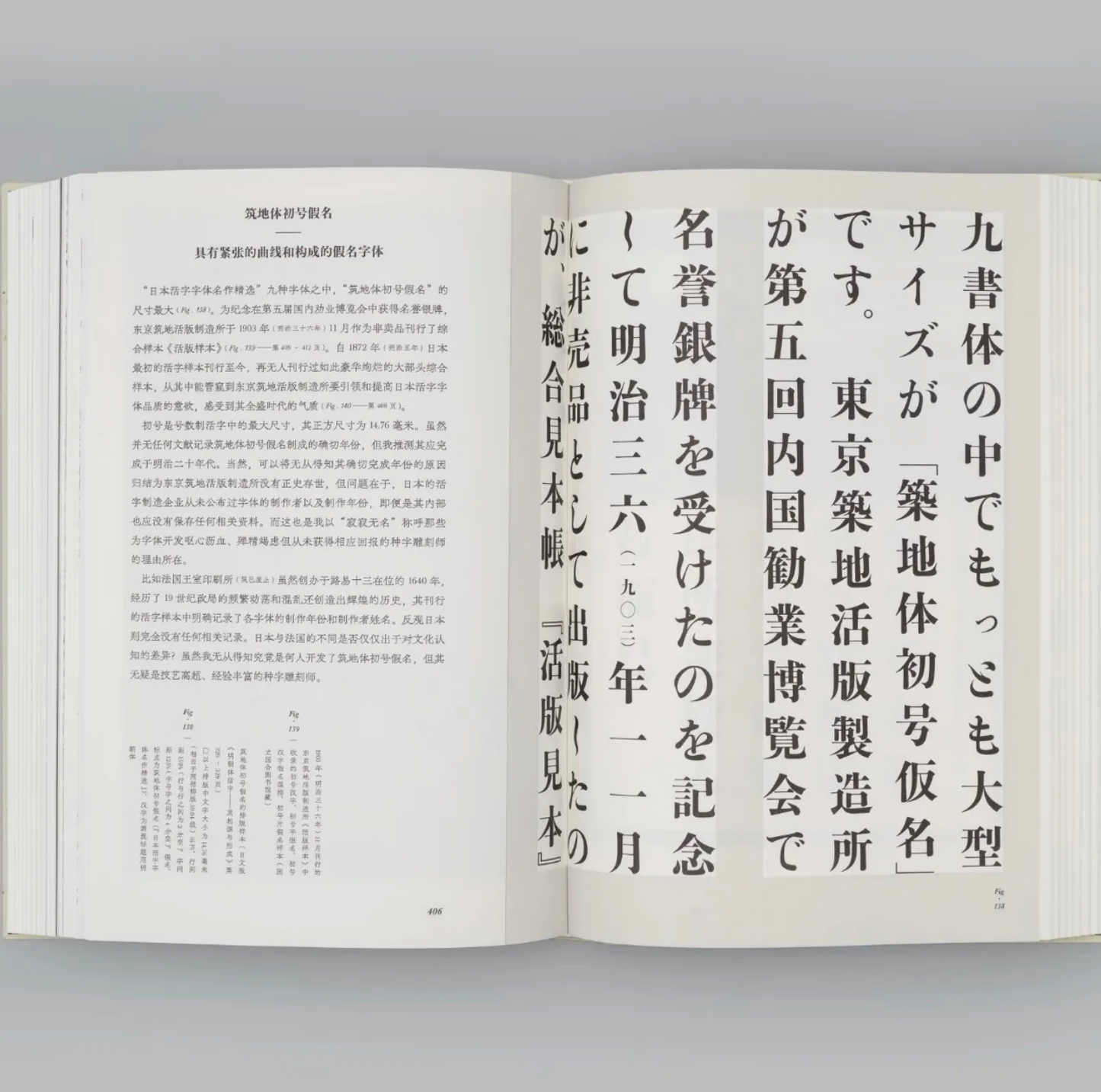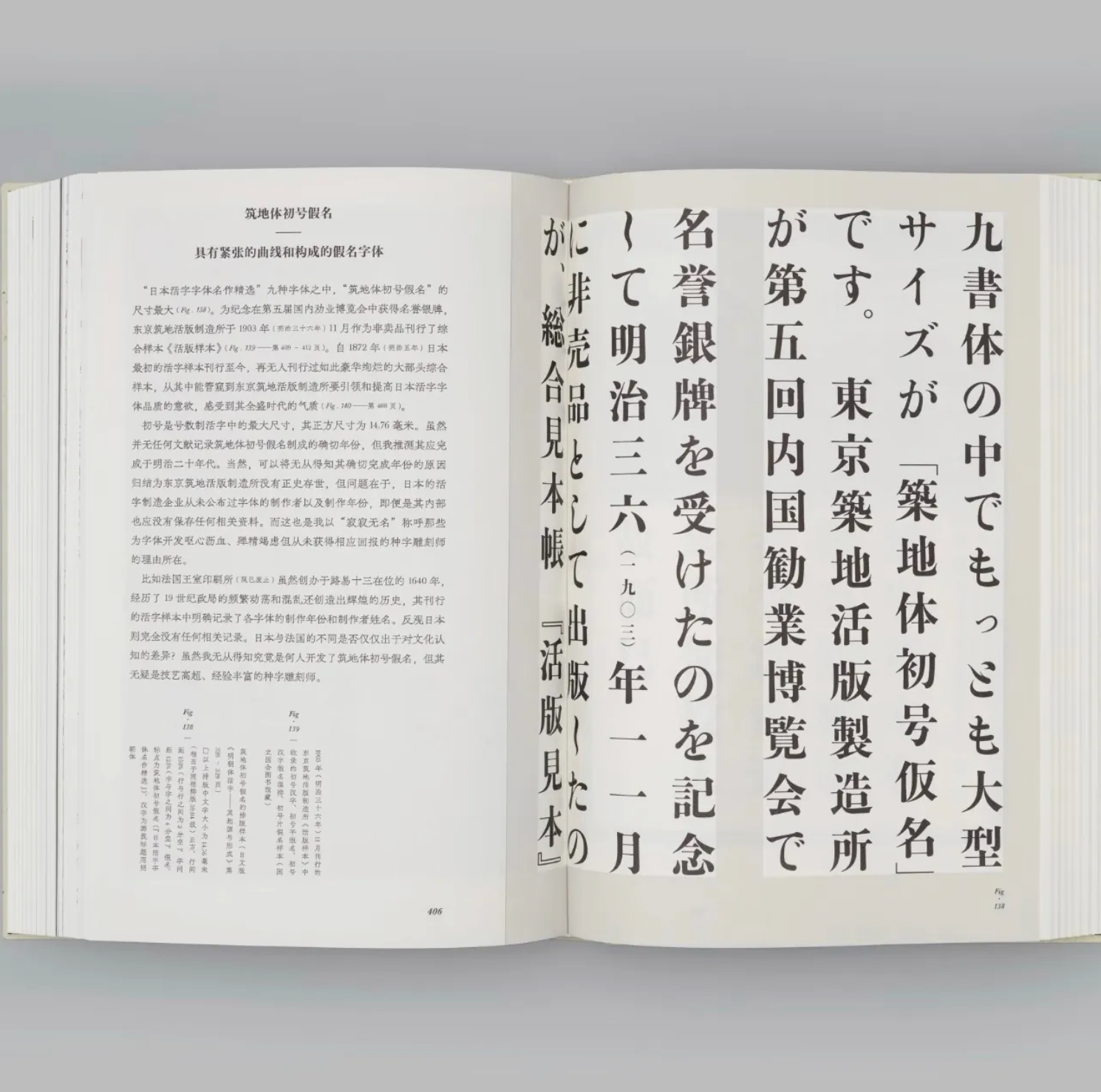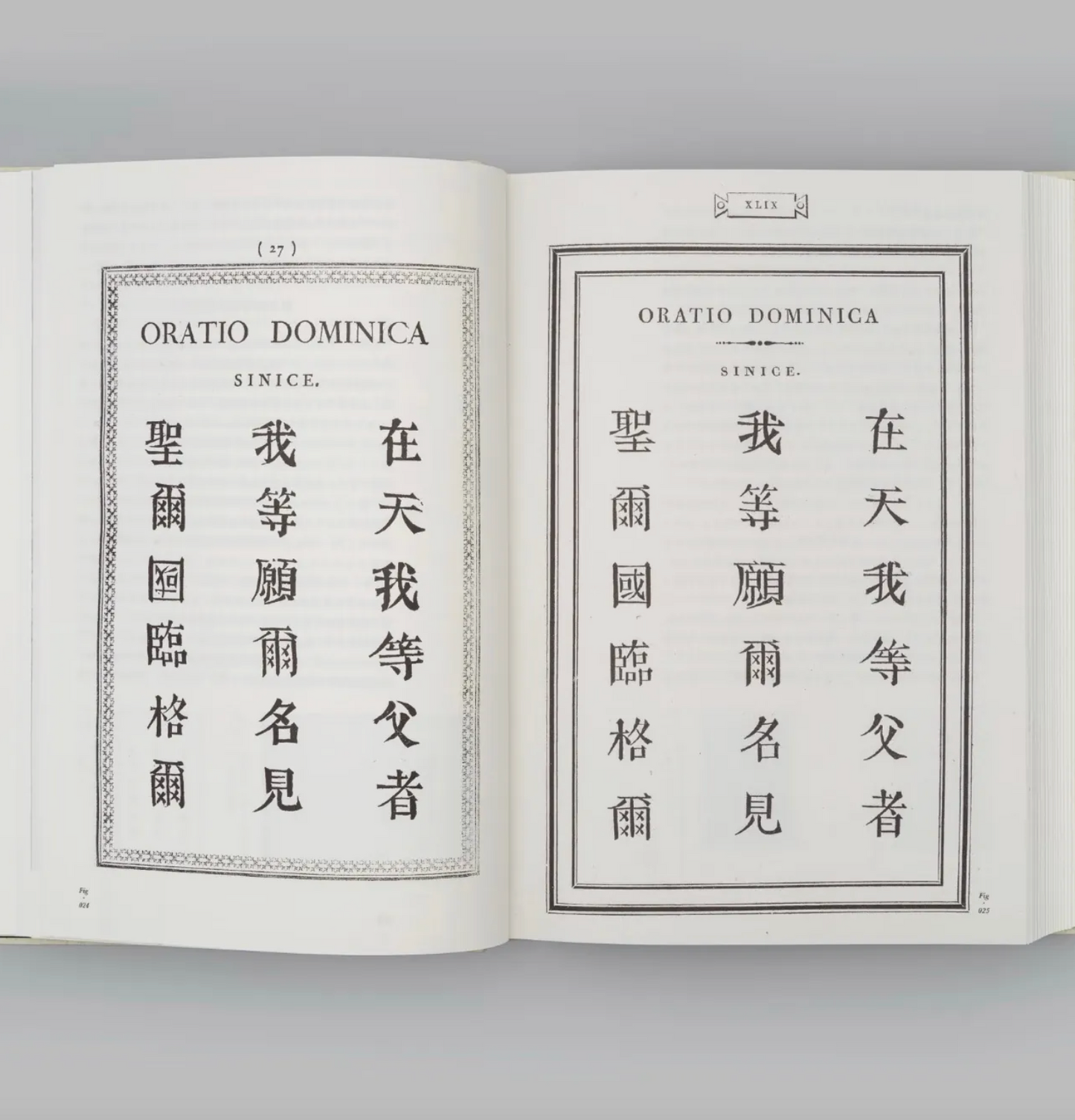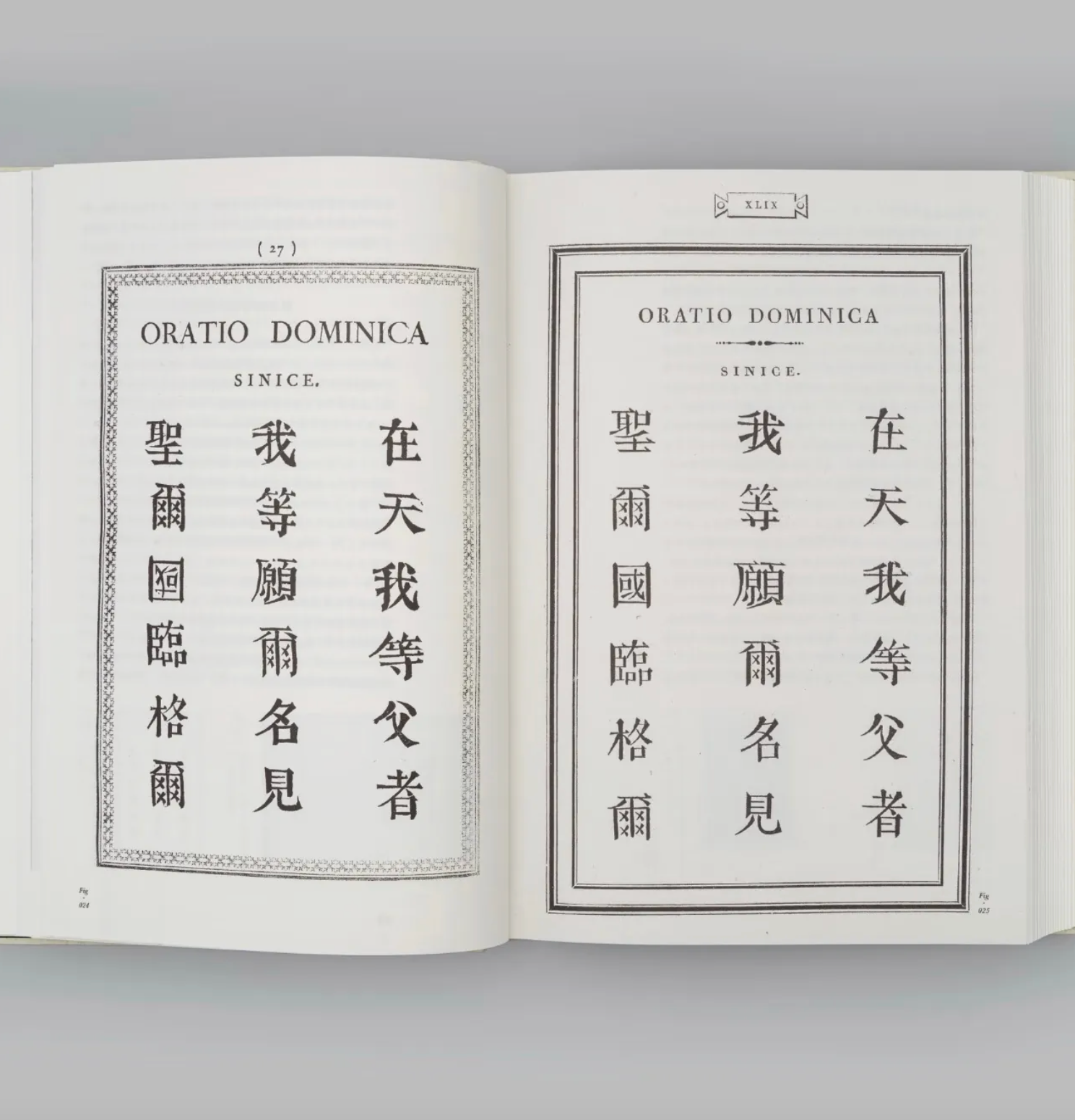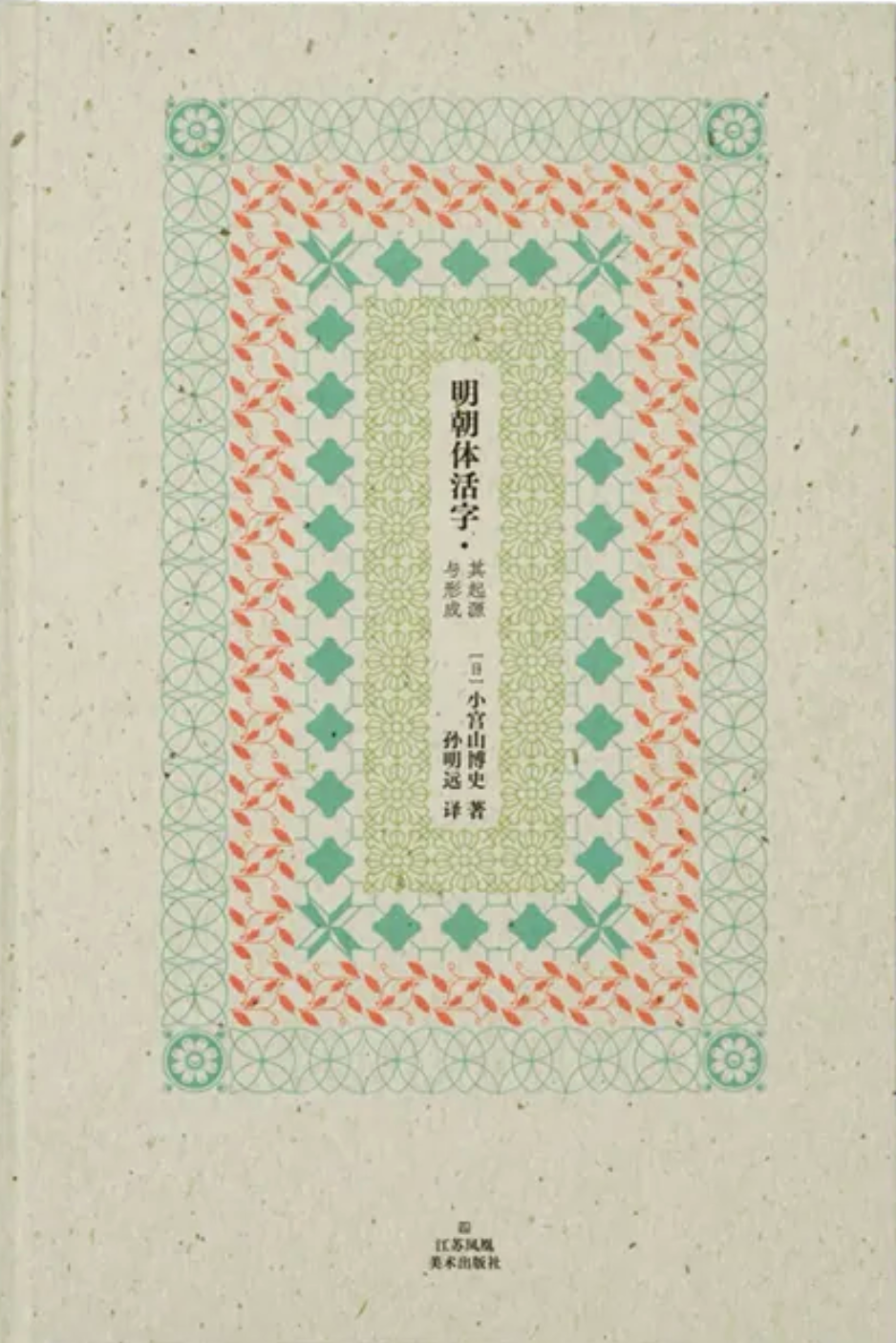
明朝體活字:其起源與形成
這本由曲閔民、蔣茜策劃並設計,孫明遠翻譯的小宮山博史著作,是一部全面呈現明朝體(宋體)歷史與發展的權威之作。作者以詳實的史料為基礎,通過對關鍵事件、重要人物及核心文獻的深入解析,系統而生動地勾勒出明朝體(宋體)在全球化進程中的起源、演變與傳播路徑。
全書展現了眾多先賢在明朝體(宋 體)發展過程中的探索與貢獻,揭示了其在技術革新與文化傳承之間的交鋒與融合,以及與東亞傳統文化精神之間的深刻關聯。書中所附的大量原尺寸珍貴圖像,進一步增強了研究的直觀性與史證力,為讀者深入理解這一字體的歷史脈絡提供了堅實依據。
此外,作者還結合自身實踐,對明朝體(宋體)的覆刻提出了具有前瞻性的見解與實操經驗,使本書不僅具備深厚的學術價值,也具有現實的指導意義。